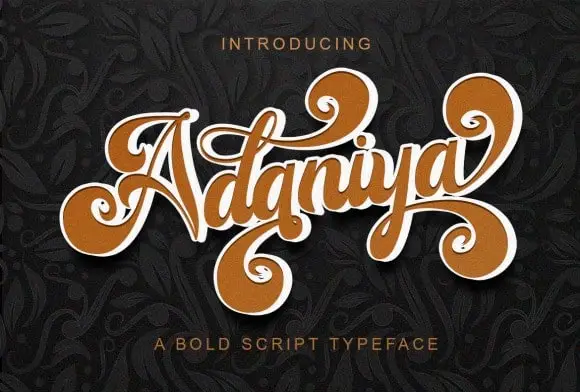
Adaniya Bold Script Font – Download Grátis
Adaniya Bold Script é uma fonte elegante e moderna inspirada por letras luxuosas. Essencialmente, essa fonte foi projetada para dar um toque elegante a seu trabalho de headlines e logotipo. Suas linhas têm texturas suaves e são cuidadosamente moldadas para criar um ar sofisticado em seus designs. Esta font se destaca por sua força, confiança e dinamismo, adicionando ao seu design uma dose surpreendente de nostalgia. Não importa qual projeto você está trabalhando, Adaniya Bold Script é uma escolha perfeita para dar um toque único à sua marca visual, tornando seus headlines e logotipos ainda mais memoráveis.